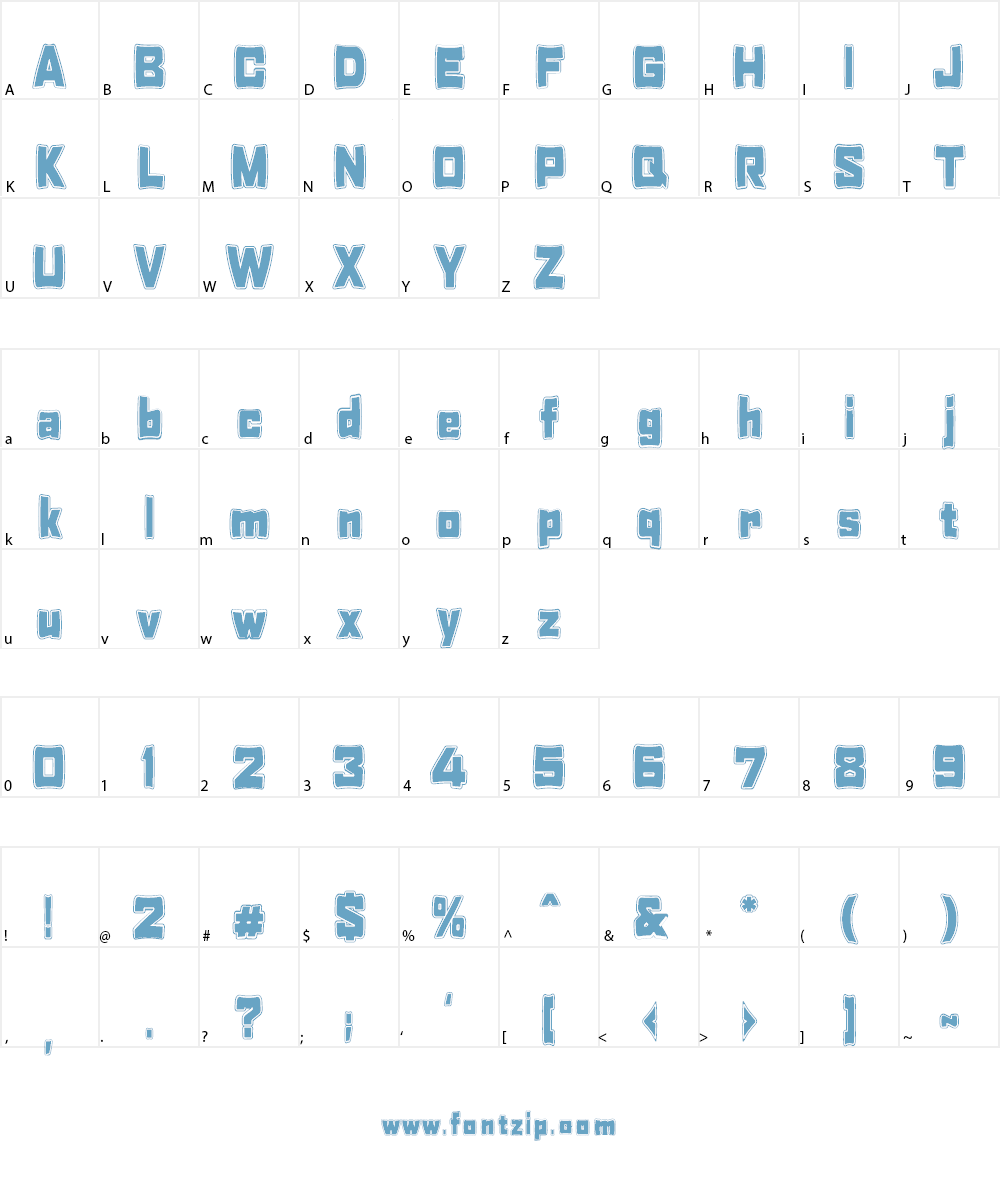
Tabaquera es una versión college de mi anterior fuente Hooby of night y segunda variante después de Rabanera, esta tipografía de estilo universitario y caracter divertido es una buena opción para el diseñador gráfico y la composición de títulos y rótulos y también para el diseño gráfico de cualquier pieza publicitaria, carteles, posters o afiches tipográficos, etc., que se quiera distinguir con el uso de tipografías modernas y exclusivas.